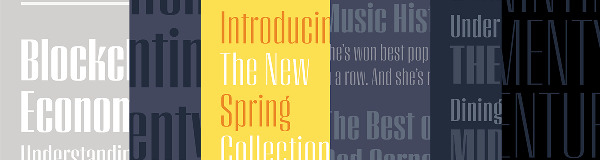
奇抜すぎないけれど印象的!フォントPeristyleを取り入れてみては?
Peristyle(peristylylum)とは、ギリシア建築やローマ建築における、柱のあるポーチ、または中庭を取り囲むコロネードで中央に庭園などがあるもののことです。時代の重要な要素であるPeristyleは、古代ローマ社会を特徴付けていました。
フォントPeristyleは、印象的ではありますが、奇抜すぎず、控えめすぎず、堂々とした書体となっています。プリント用に設計された凝縮された高コントラストのサンセリフは、スクリーン上でもすばらしく見えます。
Peristyleはヘッダー用のフォントです。 LightからBlack、Peristyle Stencil、クロマチックタイポグラフィ用の2つのレイヤースタイルの6つのウェイトがあります。
エキセントリックではなくエレガント
Peristyleは、レトロまたはsci-fiフォントとは別個のフォントになります。建築のようにドラマ、エレガンス、スタイルを作り出しますが、派手になりすぎることはありません。
さらに、Peristyleは、読者を惹きつけるためにいくつかの機能を追加することで、ほとんどのコンデンス体にありがちな繰り返しのジェスチャーパターンを回避することができます。
Stylistic Sets
PeristyleはOpenTypeのStylistic Sets機能も活かしています。Glyph alternatesを検索して手動でOpenTypeフォントのテキストに挿入する代わりに、関連するアルファベットをグループ化して、選択したテキストを一度に挿入することができます。現代のほとんどのアプリはこの機能をサポートしていますので、本文の中でPeristyleを使用することを望む人にとっては時間を節約できます。
Peristyleには「商用」のアンパサンドが含まれており、デザイナーはテキスト内のシンボルをより適切に表示することができます。
コロンの代替デザインも高い評価を得ています。コロンがベースラインに配置され、小文字の位置とスケールに位置合わせされた標準オプションとは対照的に、代替バージョンでは、コロンを大文字の中央に配置します。タイムテーブルやその他の数字を設定するときなどに使うと良いでしょう。
カラーバランス
カラーバランスは、コントラストや個性、独自性などを加えるための最も効率的なタイポグラフィ技術の1つです。交互の色調の二次的なリズムを作成したり、要素を強調したり、デザイナーのメッセージに読者の関心を引きつけたりするのに使用できます。ワードマークや見出しをデザインする際のテクニックですが、経験豊富なデザイナーでもエラー起こしやすくなります。
よくあるエラーの一つに、ひとつの文字に色が集中してしまうというものがあります。通常、文字は左右に分割されています。例えば、文字に2つの色を使用する際、その文字が2つに等分できるような場合は問題ありません。しかし、画数の少ない文字(i、l、tなど)や複雑な文字(m、wなど)の場合はコツがいります。
Peristyleの書体には、この問題を解決するステンシルデザインが付属しています。スタンドアローンのPeristyle Stencilフォントに加えて、2色のレイヤードスタイルも用意されています。レイヤーされたスタイルは、異なるトーンで色付けされ、ライン全体の色のリズムやバランスを保つために積み重ねられます。 Peristyle Stencilは色のタイプを自動的に逆にするように設計されています。
言語サポート
PeristyleのクリエイターであるHoefler&Co.は、ライブラリをOpenTypeに移行しています。また、OpenTypeフォントは文字数が事実上無制限であるため、Hoefler&Co.は2005年にLanguage Research Programを作成して言語カバー範囲を拡大しました。この研究の初期製品はLatin-X™文字セットです。タイプファウンドリーの領域を、世界中の2億人の読者にまで拡大するセットは、今日の社会における言語と文化を反映しています。